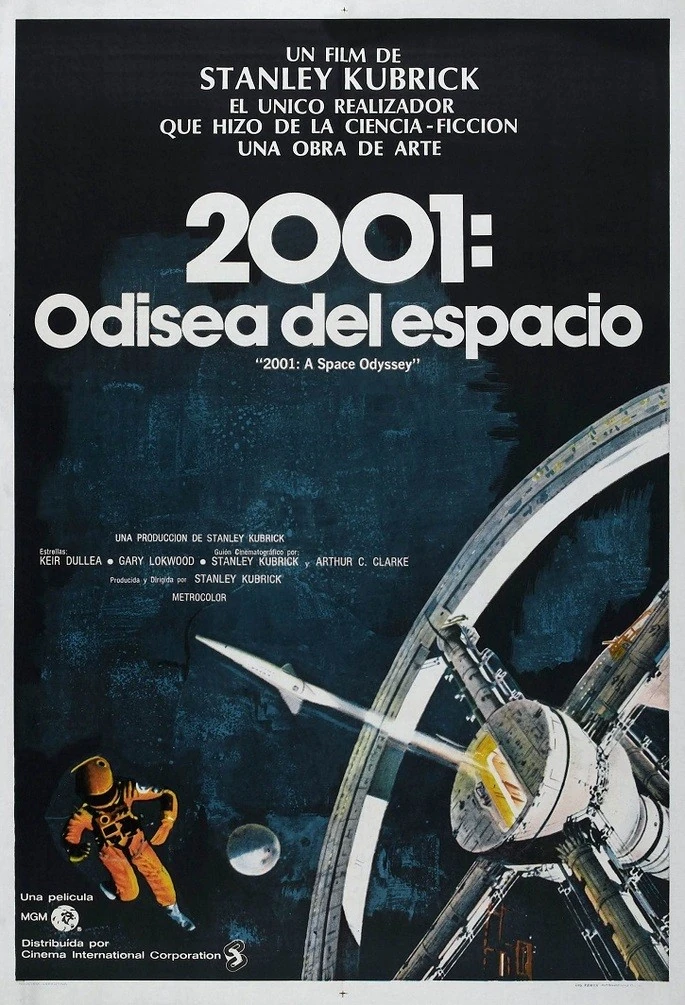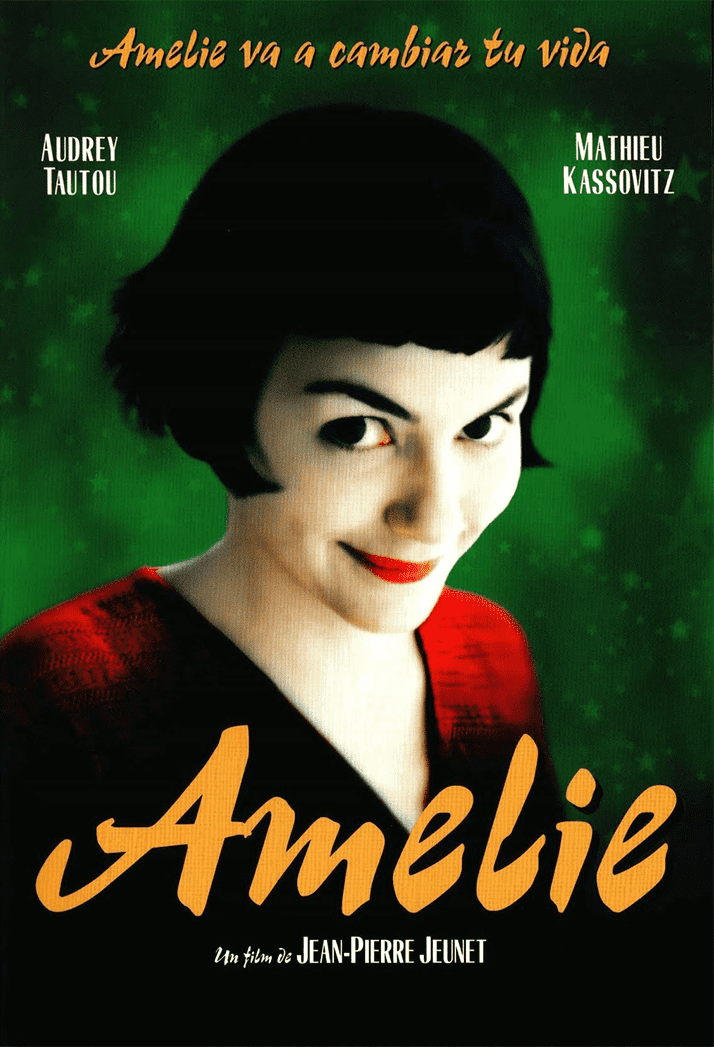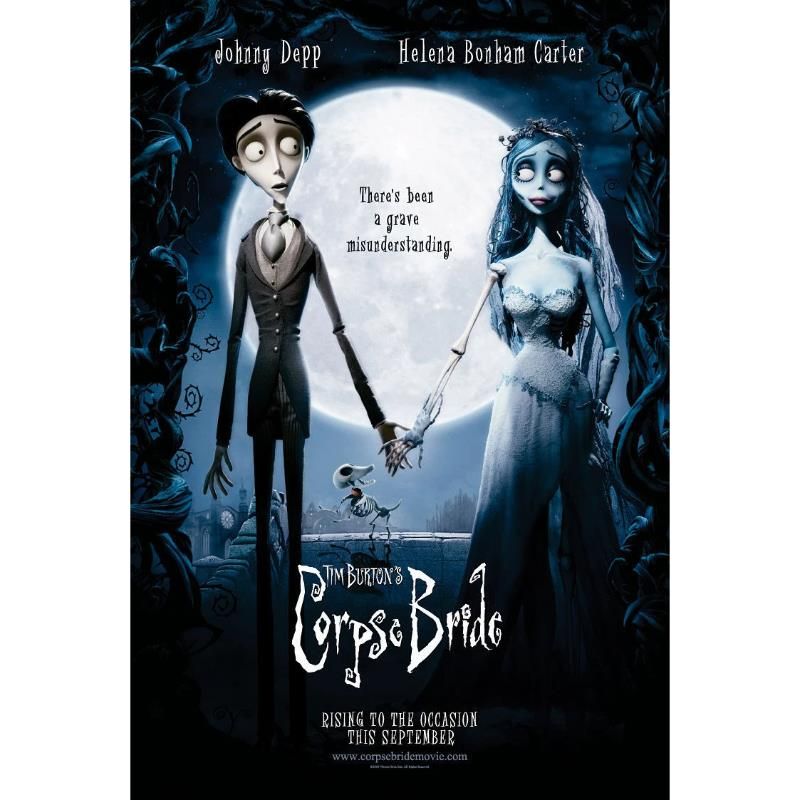
15 tipografías de película
Conoce las fuentes tipográficas usadas en pósters, material promocional y créditos de grandes películas
Todos los amantes de la tipografía saben que una de sus aplicaciones más llamativas y emocionantes está en el cine. Desde que vemos el tráiler de una película o nos encontramos con su cartel, hay ciertos diseños que captan de inmediato nuestra atención y nos hacen desear ver la producción enseguida.
Recopilamos una lista de 10 películas con un uso excepcional de tipografías. Compartimos contigo el nombre de los diseñadores y agencias que trabajaron en el producto final, así como las fuentes que usaron —cabe notar que en algunos casos las tipografías fueron ligeramente modificadas—.
Vertigo (1958)
El legendario diseñador Saul Bass creó los títulos de esta espectacular cinta de Alfred Hitchcock. Como en muchas de sus otras creaciones, estos créditos son un ejemplo espectacular de la armonía entre tipografía y vídeo que solo el gennio de Bass pudo lograr.
El trabajo de estos créditos sentó las bases para una nueva escuela de diseño de títulos fílmicos. La secuencia en espiral es obra de John Whitney, uno de los pioneros en la animación computacional, bajo la guía y dirección de Bass.
Tipografías principales: Claredom y News Gothic.
The Grand Budapest Hotel (2014)
Wes Anderson obtuvo la aclamación de la crítica internacional por esta película, que destacó por su diseño de producción, fuertemente influenciado por la tipografía.
Los diseños del cartel, así como empaques, estampillas, pasaportes, periódicos, menús e incontables props más vistos en ella, son obra de Annie Atkins.
Tipografía principal: Archer.
Otras tipografías usadas en la película: Beaufort, FF Din, Old English, Münchner Feature, Trajan, Russian y Cheltenham.
Lost In Translation (2003)
En este drama clásico de Sofia Coppola el diseñador Corey Holms usó para el póster y material promocional un diseño simple y una tipografía sobria, muy acorde con la introspección que caracteriza a los personajes en su estancia en Japón.
Tipografía principal: Kabel.
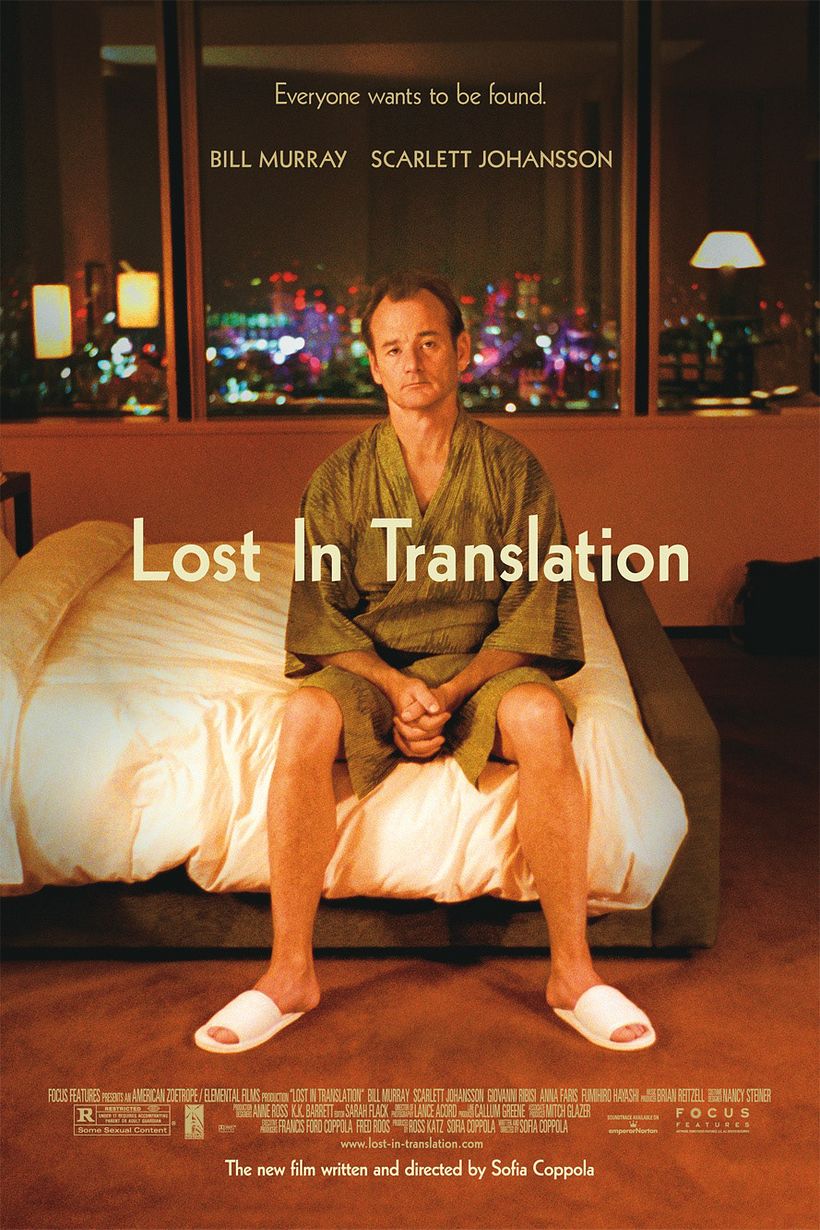
The Lobster (2015)
La aclamada y extraña película de Yorgos Lanthimos se promocionó con hermosos carteles minimalistas, creación del diseñador Vasilis Marmatakis.
Tipografía principal: Avenir Next.
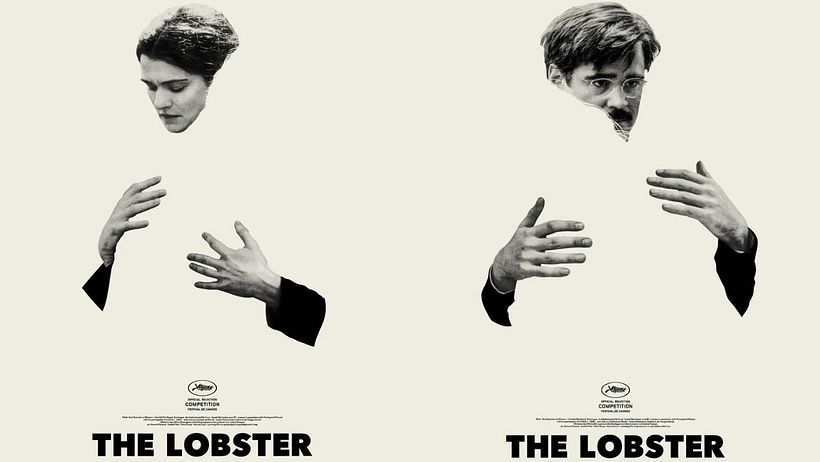
Inherent Vice (2014)
Esta cinta de culto de Paul Thomas Anderson se caracterizó por su llamativo cartel y secuencia de créditos. Desde los primeros segundos colores neón nos transportan al escenario decadente de Los Ángeles en los años setenta.
El diseño estuvo a cargo de BLT Communications y los diseñadores Tal Goretsky, Darshan Zenith, Darren Haggar, Dustin Stanton y Steven Chorney.
Tipografías principales: Drescher Grotesk, Rolliing Pen, Ne10, Sneaker Script, ITC Serif Gothic.
Julieta (2016)
Este desgarrador filme de Almodóvar estuvo nominado a distintos premios internacionales. Como es costumbre en su obra, nos sumergimos en un universo profundamente femenino, pero que retrata la maternidad con una visión fresca.
El diseño del póster y de los créditos es obra de la agencia Barfutura.
Tipografía principal: ITC Grouch.
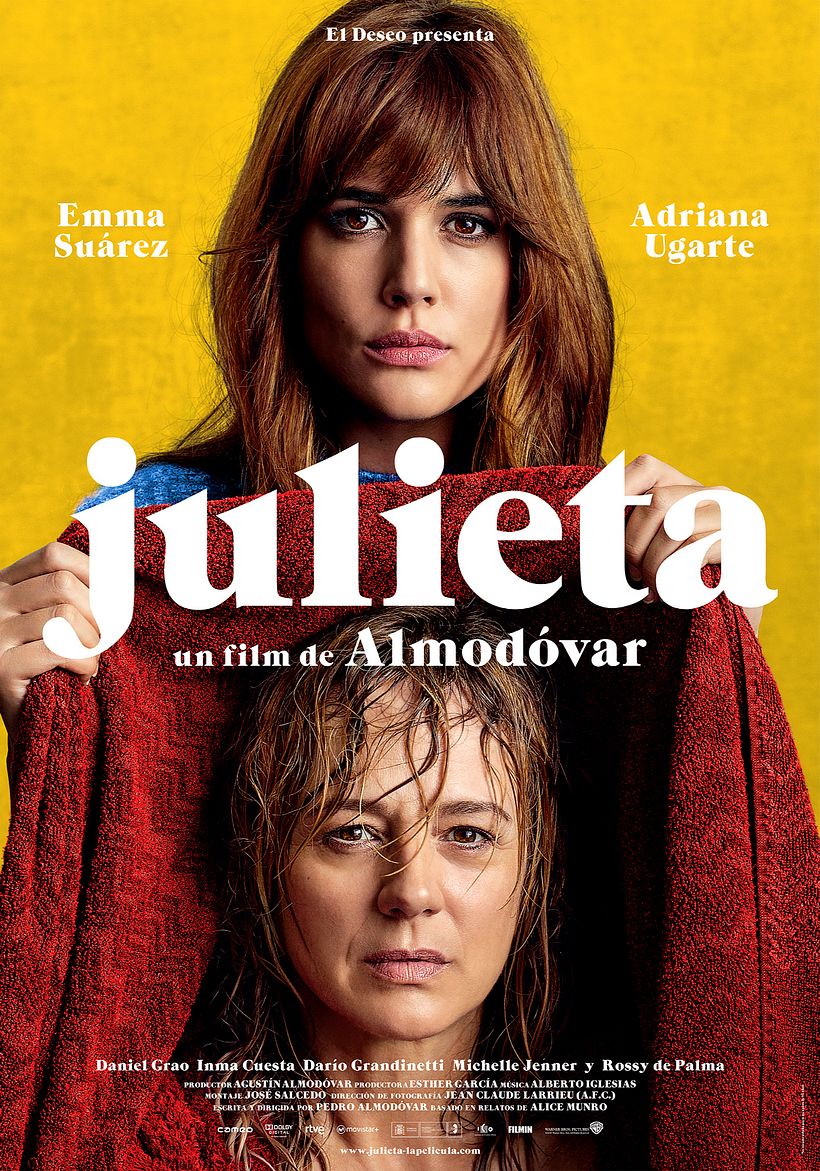
The Big Lebowski (1998)
La película de los hermanos Coen dejó muchos de los personajes y diálogos más célebres de la historia del cine.
También es célebre por sus increíbles títulos de créditos al inicio y final, que en verdad hablan del carácter de toda la cinta, y se reflejan en algunas de las secuencias más importantes. Los diseñadores fueron Big Film Design y Randall Balsmeyer.
Tipografías principales: Magneto, Mesquite, Monoline Script, Berthold Block.
Parasite (2019)
Sin lugar a dudas la película más discutida de 2019, creación del director Bon Joon-ho.
Tanto los créditos como los carteles oficiales se hicieron con un diseño modesto y clásico, en el que se prefirieron fuentes igualmente clásicas y resistentes al paso del tiempo. No hay créditos del diseñador del póster original y títulos.
Fuentes principales: Gotham, Garamond, LT Didot.
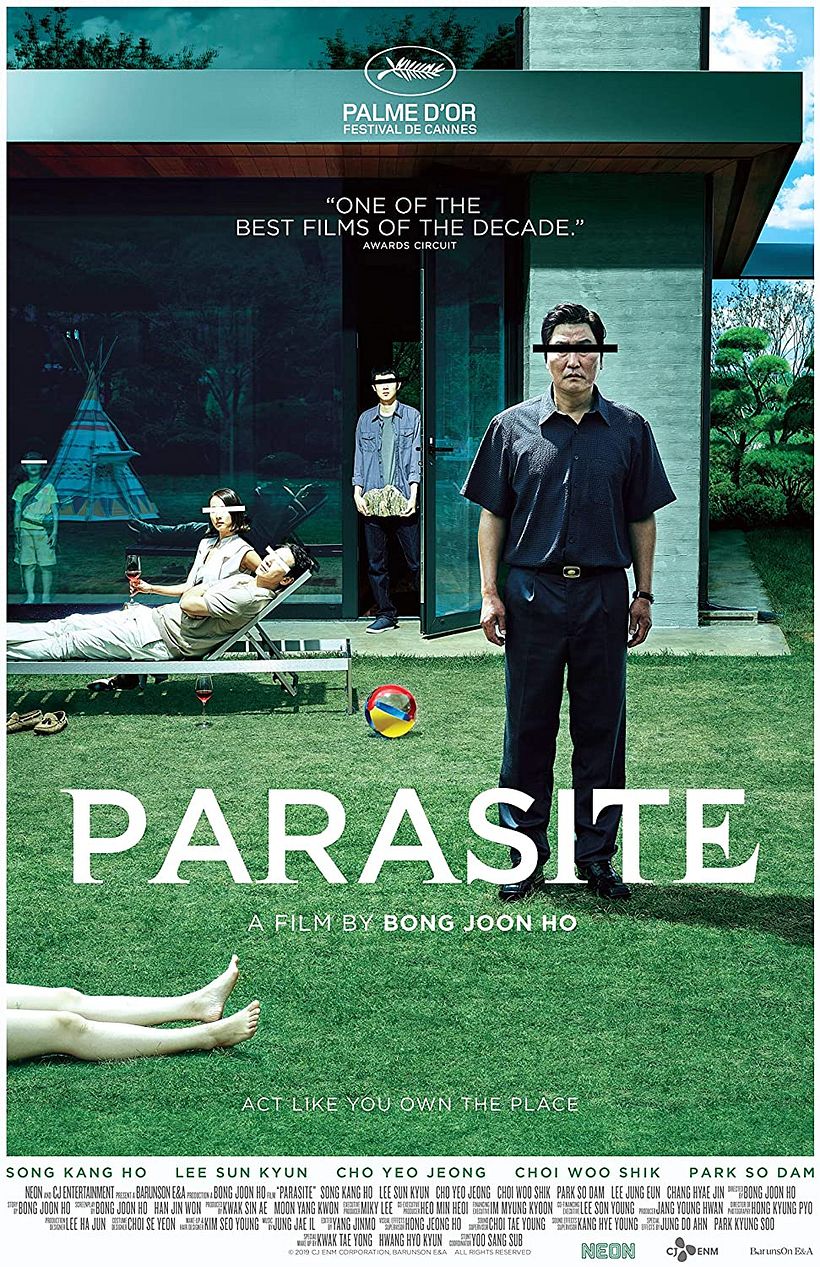
I’m Still Here (2010)
Este falso documental dirigido por Casey Affleck llegó a oídos de todos los amantes del cine. En él, Joaquin Phoenix anuncia su supuesto retiro del cine.
El cartel tuvo también una gran repercusión en la cultura popular, y vimos muchos proyectos que trataron de capturar el estilo de tipografía itálica cortada. El cartel (y los títulos) son obra de Neil Kellerhouse, Michael Muller y Erik Buckham.
Tipografía principal: HTF Didot.
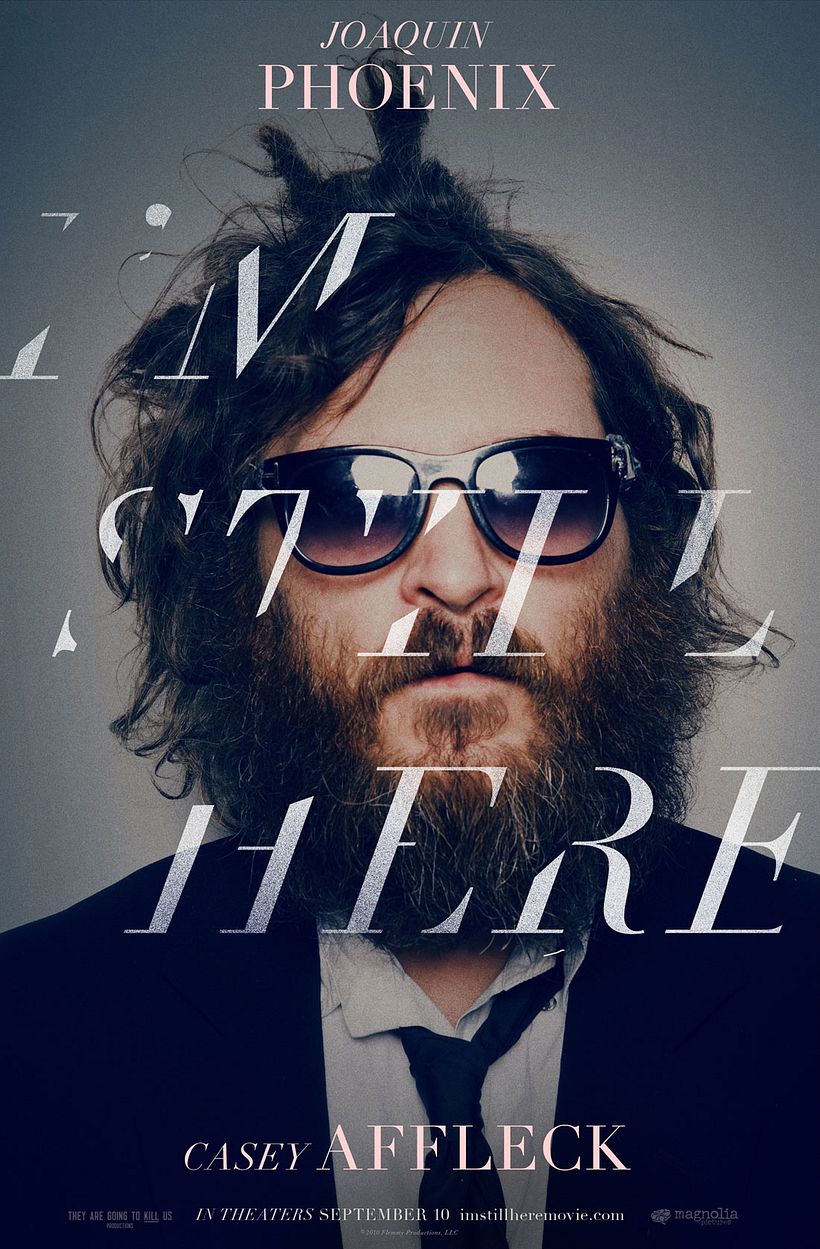
Jackie Brown (1997)
El filme de Quentin Tarantino es un homenaje al cine de los setenta, y como tal, su uso de la tipografía transporta a un universo completamente funky.
Se usaron fuentes diseñadas en los años 70 para los carteles, material promocional y títulos. El diseño es de Pacific Title y Mirage.